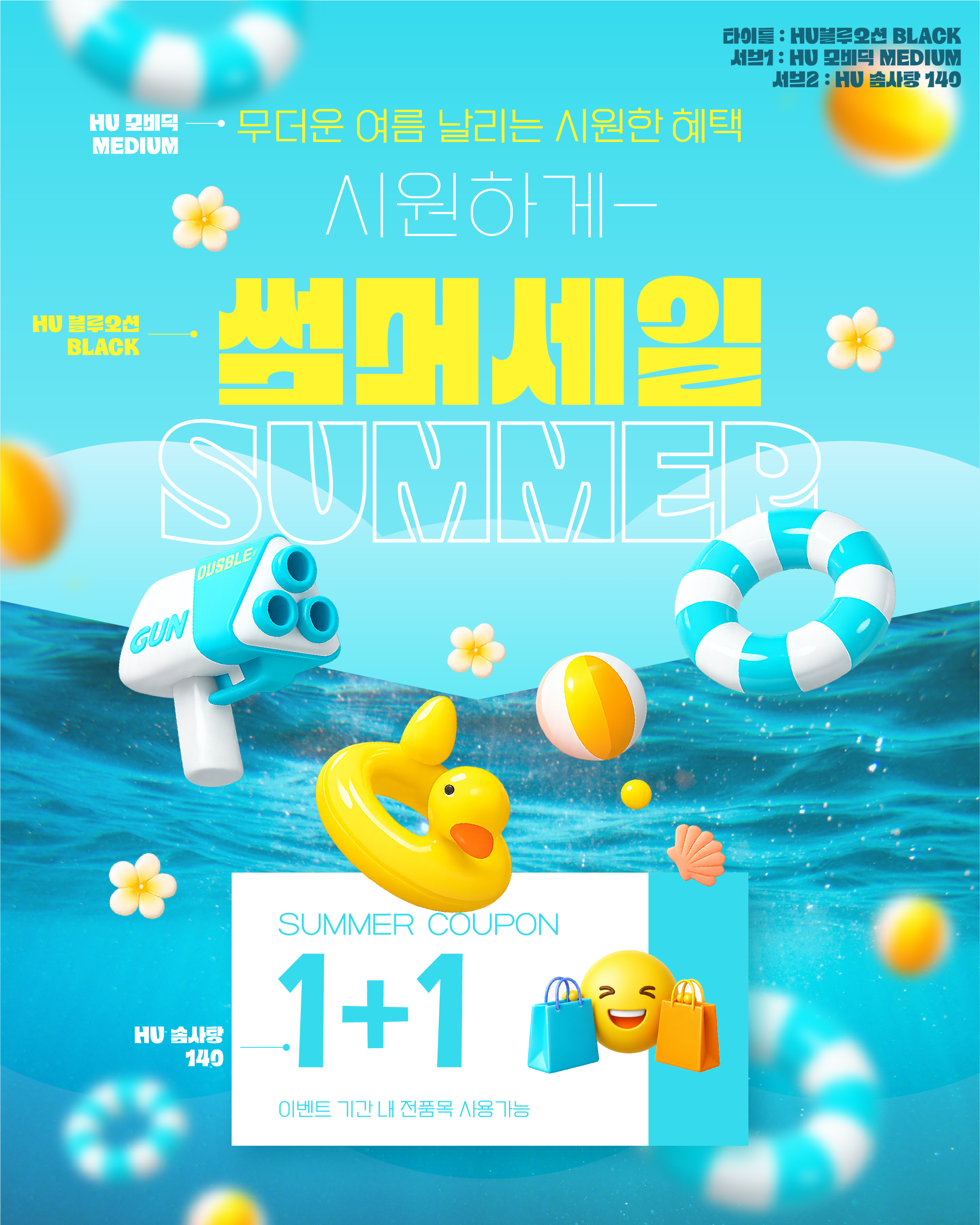
#본문HU모비딕 패밀리 확장팩
정사각형의 모듈을 한, 넓은 공간 구성이 돋보이는 본문용 고딕 서체.
(패밀리 확장팩_5종)
폰트      HU모비딕 패밀리 확장팩
굵기      5종
* 모비딕   Hairline
* 모비딕   Thin
* 모비딕   Light
* 모비딕   Regular
* 모비딕   Medium
구성      KS한글 11,172자